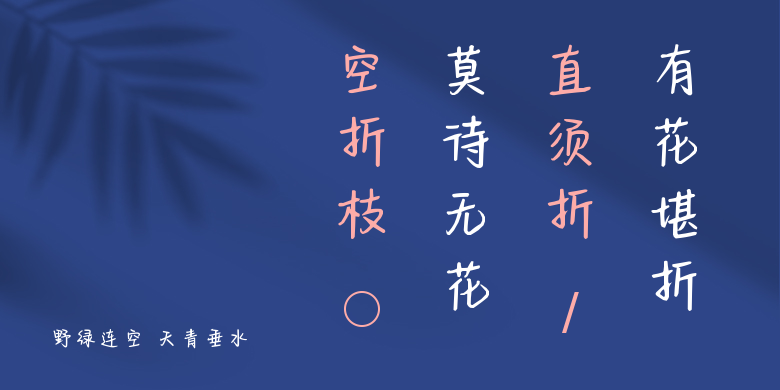
野绿连空 天青垂水
野绿连空 天青垂水,这款字体结构工整、笔画清晰,兼顾美观与易读性,适用于标题、正文、海报、包装、LOGO 等多种场景。字形优雅稳定,风格百搭耐看,适配日常排版与创意设计,让文字呈现更舒适、更具质感。野绿连空 天青垂水一笔一画,皆是细节,以均衡的比例、流畅的线条打造舒适视觉体验,字形端正大气,风格简约现代。无论是商业设计、品牌宣传还是日常排版,都能轻松驾驭,让文字更有格调与力量。野绿连空 天青垂水字体下载。